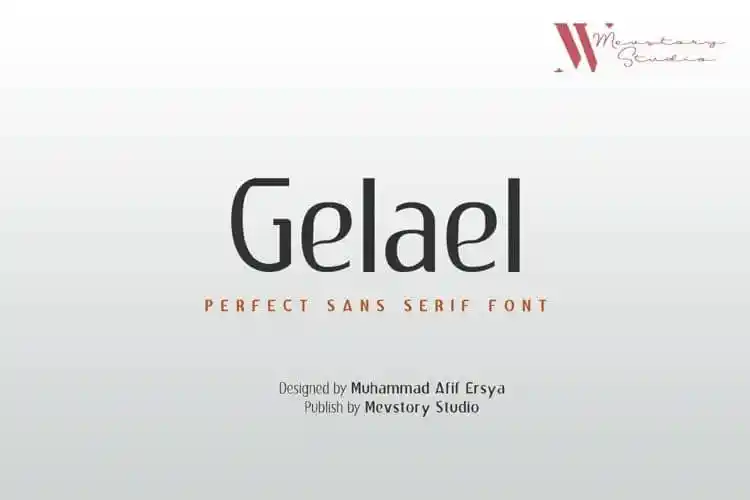
Gelael Sans Serif Font
Gelael Sans Serif é uma elegante tipografia sans-serif minimalista e moderna criada pelo designer mhdafifersya. Esta fonte não tem serifas, mantendo assim uma aparência clean e leve, perfeita para ambientes de design contemporâneos. O uso da Gelael Sans Serif pode transformar elementos como logotipos, cartões de visita, embalagens, revistas, convites de casamento ou anúncios em experiências visuais intrigantes e sofisticadas. Se você busca uma fonte elegante que combine modernidade com simplicidade, Gelael Sans Serif é a escolha perfeita. Suas linhas clean e clara lhe permitirão criar design com alto padrão, de logotipos profissionais até textos informativos em embalagens de produtos ou mensagens publicitárias. Com sua ampla gama de caracteres que inclui letras maiúsculas e minúsculas, números, pontuação e símbolos, a Gelael Sans Serif se adapta facilmente para um amplo espectro de projetos gráficos, desde revistas até cartões de aniversário. Não perca tempo, transforme o seu design em algo excepcional com a Gelael Sans Serif, uma fonte que não apenas destaca sua marca, mas também oferece estilo e elegância.